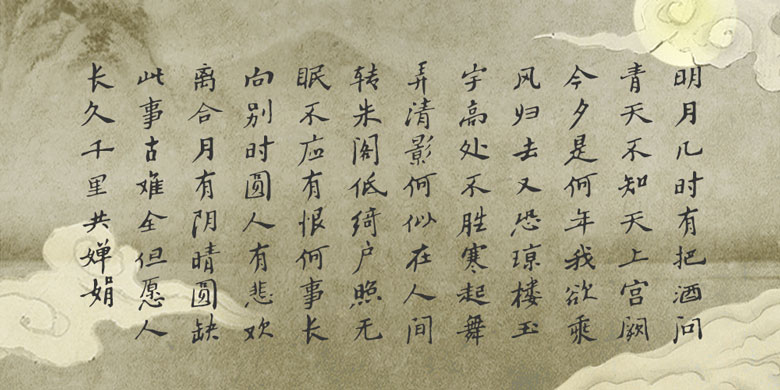
品牌:方正字库书体坊设计师:禚效锋发行时间:2019字库编码:简繁扩展(GBK)、大陆简体(GB2312-80)分类:常规书写·毛笔字体属性:精品字
郑板桥,清代书画家,“扬州八怪”之一。其书法艺术在中国书画史上独树一帜。他的楷书学《瘗鹤铭》、黄山谷、王羲之、王献之,写得清新亮丽;并且能够参以隶书的波磔、篆书的结构、行草的用笔,自称“六分半书”,以楷、隶为主,把楷、草、隶、篆四体融为一体。他以兰草画法入笔,这是他在书法艺术上大胆独创,在结体上进行夸张,使长窄的字更加长窄,宽的更宽,斜的更斜;章法布局上,富有节奏韵律感,开创了书法历史的先河。本字体,由书体坊禚效锋集郑板桥楷书代表作制作而成,是一款优秀的书法字体。